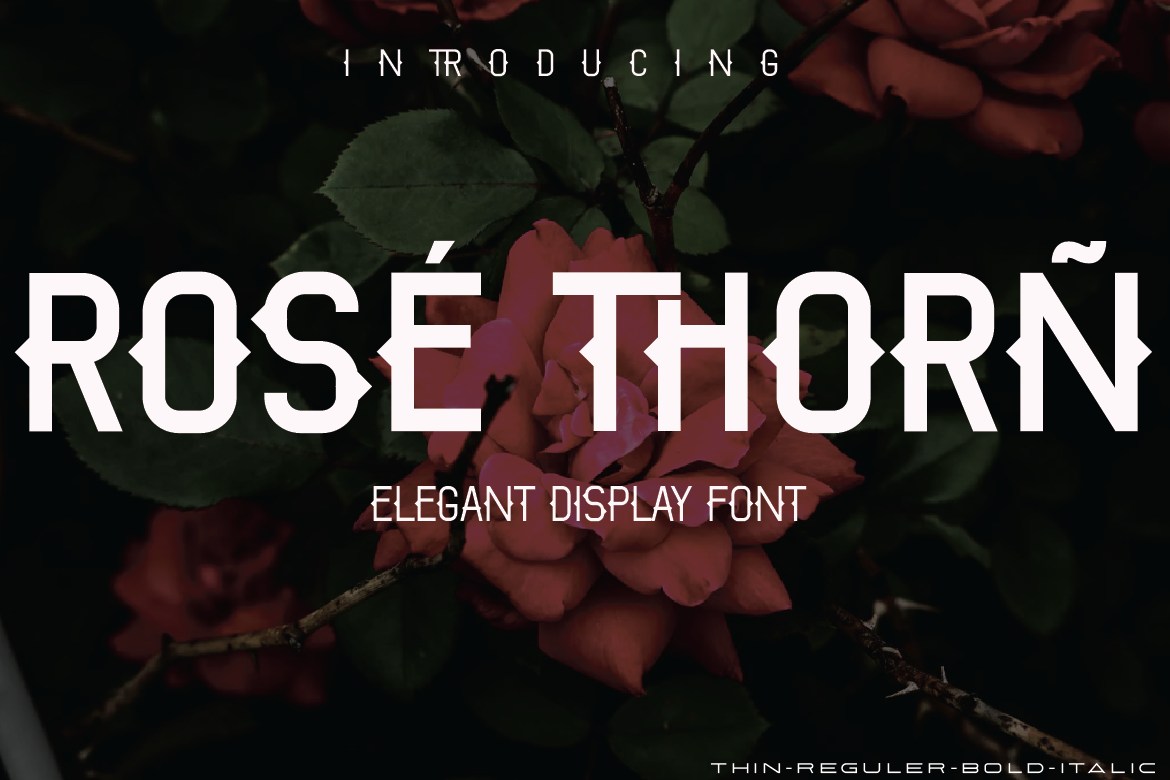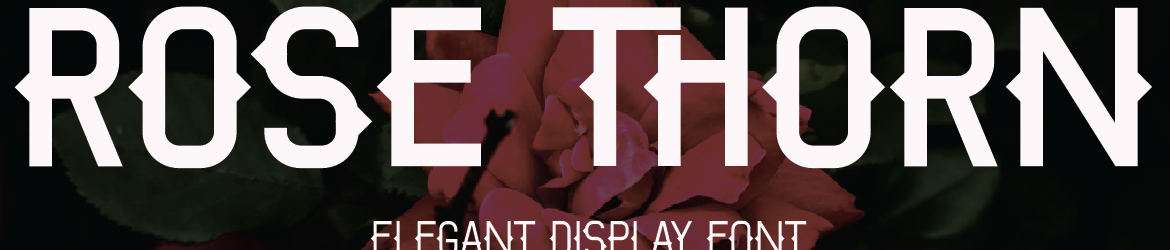
A fonte Rose Thorn é uma elegante escolha para designers que buscam criar projetos visualmente impactantes. Embora leve e delicada, sua característica principal reside na presença formal e sofisticada que oferece um toque diferente de personalidade. Através da influência do design minimalista moderno, a Rose Thorn é uma fonte que transmite beleza e harmonia em qualquer projeto, mas permanece formal com seu tom respeitosamente distinto. Seu único ponto de vista original torna o tema desta tipografia único e cativante, combinando elementos de personalidade e elegância na medida certa para impressionar seus destinatários. Ideal tanto para um design minimalista quanto sofisticado, a Rose Thorn é uma excelente escolha para aqueles que buscam dar seu projeto um toque distinto, que não apenas expressa sua visão visual, mas também traz um novo ar de beleza e harmonia.